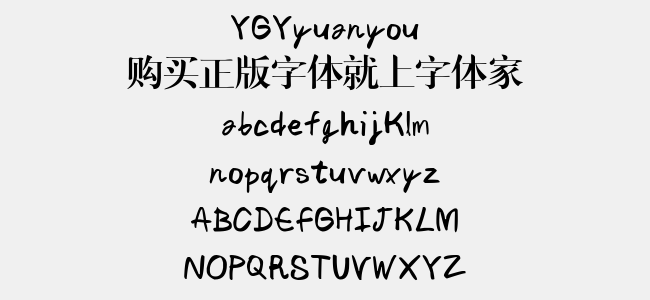
YGYyuanyou
字体作者:YGY-ywtixi
书体类型:英文类
YGYyuanyou是一款个性独特的英文字体,由YGY-ywtixi制作发布,非常适合创意类的PS字体,英文广告设计载体上使用,在设计中选择这款字体应用的话,会起到非常理想的效果。
YGYyuanyou - 大写字母/小写字母/数字